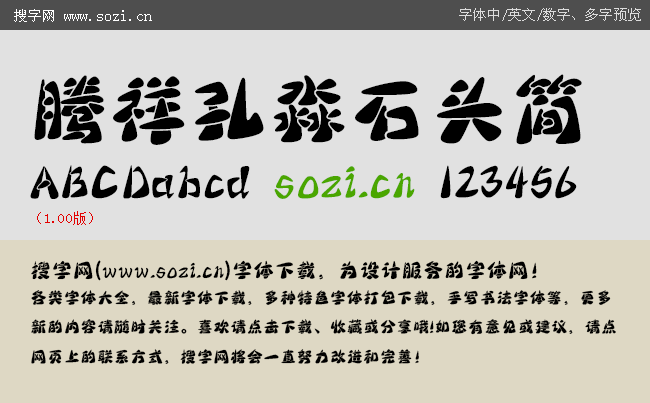
騰祥孔淼石頭簡
搜字網(wǎng)提供一款騰祥孔淼石頭簡中文字體下載,騰祥孔淼石頭簡是一款擁有卡通元素的中文簡體字體,字形上尖下寬,上粗下細(xì)、結(jié)構(gòu)美觀、風(fēng)格統(tǒng)一,可以廣泛應(yīng)用于兒童卡通、創(chuàng)意廣告、藝術(shù)設(shè)計、平面設(shè)計等應(yīng)用。